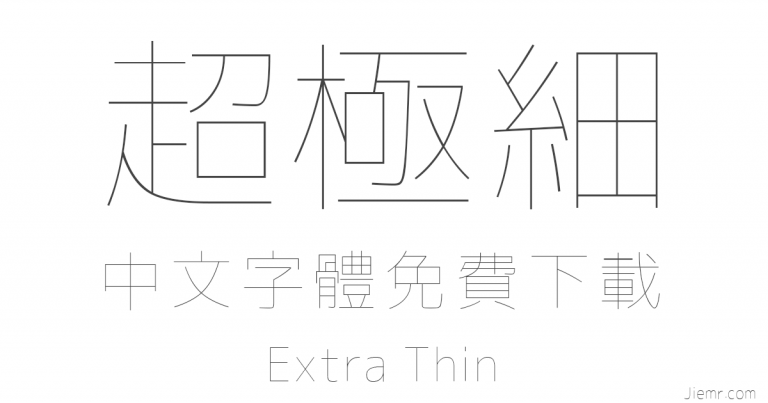
免費字體下載 Line Font 超極細黑體字型,可用於商業用途 Extra Thin 相似字
這款超細字體,可以用於商業用途使用,此外這套字體修改日本免費開源黑體 M+Fonts 而成,但設計師(或團隊)並沒有留下名字。字體的英文名稱是 Line font 整個字體的線條很像用圓珠筆書寫而成的字體,整體的架構非常工整,也很秀氣,這款字體的線條非常的薄,所以使用在內文的小字很可能會變得模糊,印刷的時候會消失,這點是這款字體要注意的地方,也就是說它的使用範圍是有限制的
由於這款字體是日本人製作的日文字體,所以在中文字的使用上會有部分缺字,如果遇到缺字的部分就要自己造字了,以下是我做了幾個字